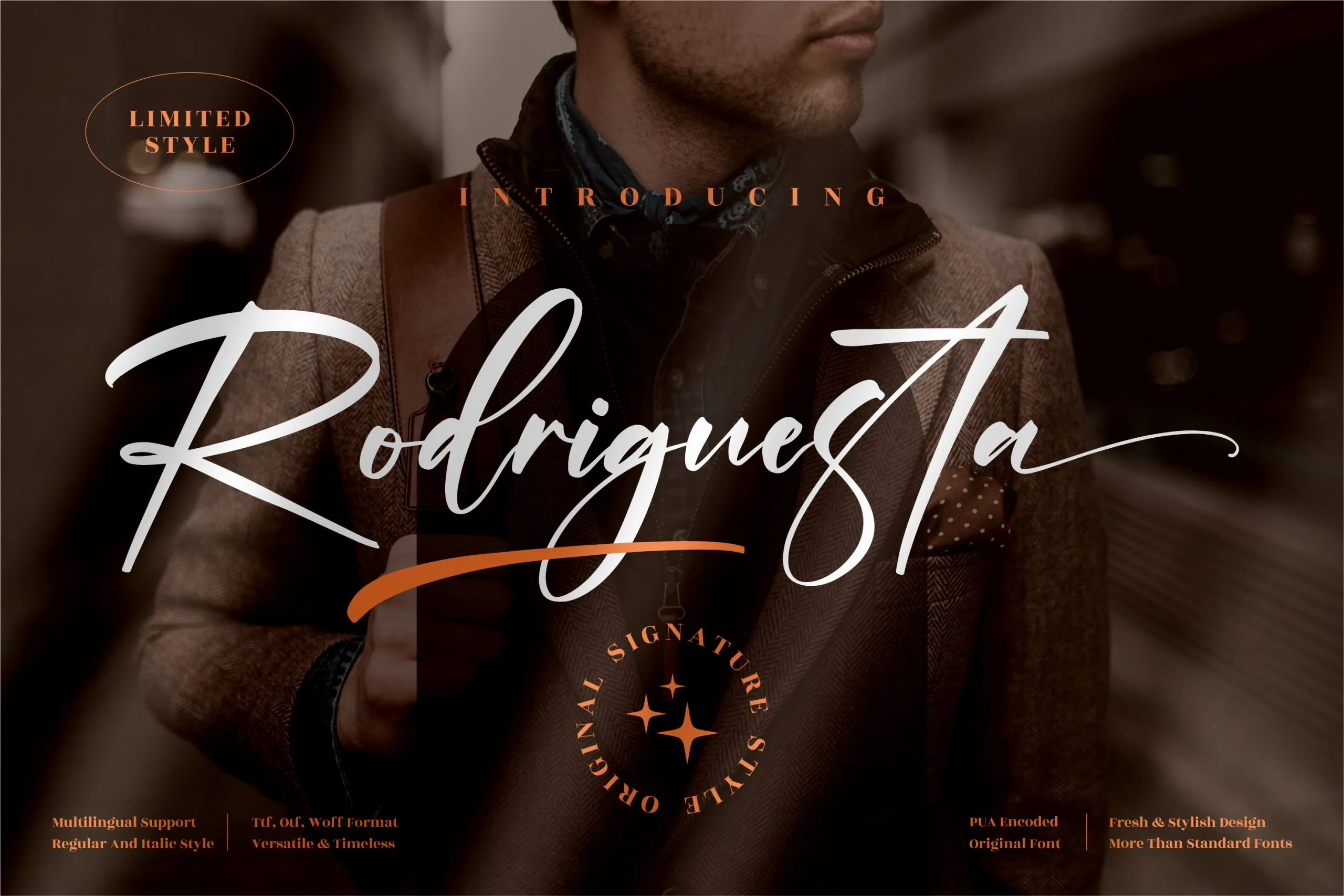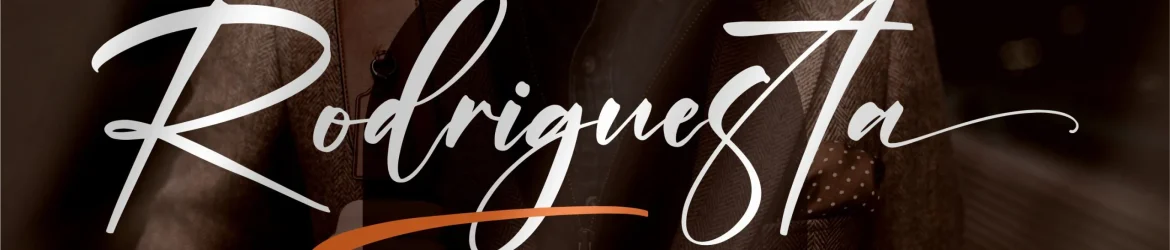
A ‘Rodriguesta Font’ é uma elegante opção para aqueles que procuram adicionar um toque sofisticado a seus projetos digitais e impressos. Desenvolvida pelo estúdio Perspectype, essa fonte é perfeitamente adaptada para uma variedade de usos, desde assinaturas de marca em produtos de varejo até etiquetas de embalagens luxuosas e design gráfico pessoal. Seu caráter moderno e autêntico torna-a adequada tanto para projetos simples quanto para aqueles que exigem um toque especial. Com uma tipografia cuidadosamente elaborada, ela oferece uma opção perfeita para estilos de texto personalizados e assinaturas profissionais. Essencial para designers gráficos e criativos, a ‘Rodriguesta Font’ é uma escolha segura para qualquer projeto que precise de um toque autêntico e sofisticado. Para os designers de produtos, especialmente aqueles trabalhando em marcas e identidades, essa fonte é perfeita para criar uma conexão emocional com seu público. Ela também pode ser usada para personalizar itens como t-shirts, cartões de visita ou camisetas que transmitam seu próprio estilo único. Independente do tipo de projeto que você esteja lidando, a ‘Rodriguesta Font’ é uma excelente escolha para dar um toque distintivo e elegante ao design.